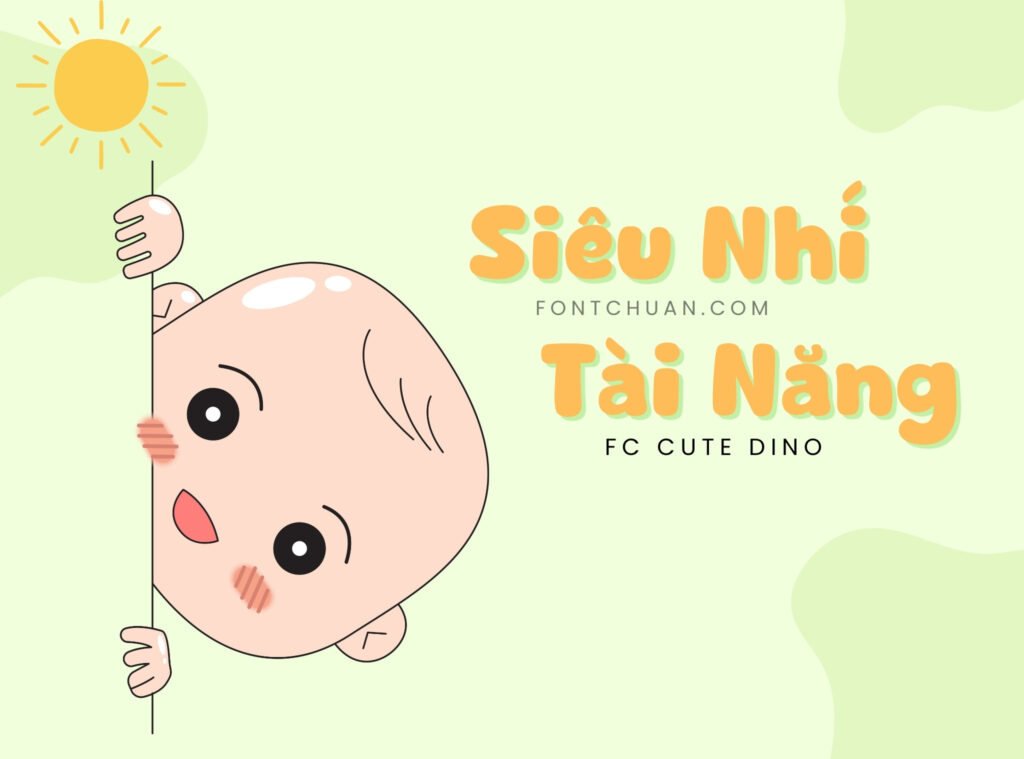
Font FC Cute Dino Việt Hóa
Tác giả Font: Khurasan
Việt hóa bởi: Font Chuẩn
Cute Dino là một font chữ hiển thị vui nhộn được thiết kế bởi Syafrizal, còn được biết đến với tên Khurasan. Font này mang phong cách hoạt hình, với các ký tự dày dặn mập mạp, tròn trịa và đáng yêu. Cute Dino hỗ trợ đa ngôn ngữ, bao gồm cả tiếng Việt, giúp nhà thiết kế tiếp cận đối tượng rộng rãi.
Về thiết kế, Cute Dino sở hữu các đường nét mềm mại, cấu trúc chữ cân đối và phong cách thân thiện, phù hợp cho nhiều mục đích sử dụng trong ngành ẩm thực, thiết kế logo, tiêu đề, poster, bao bì sản phẩm và các ấn phẩm quảng cáo. Ngoài ra, Font FC Cute Dino Việt Hóa cũng là lựa chọn lý tưởng cho các dự án font chữ Tết, như thiệp chúc mừng năm mới, lịch Tết hay banner trang trí, mang đến không khí vui tươi, đáng yêu và phù hợp với tinh thần lễ hội.